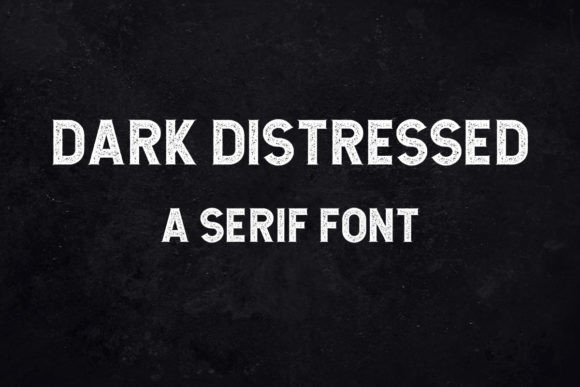
Dark Distressed
適切なデザイン要素を見つけるのは難しい場合がありますが、Dark Distressedは作品を即座に引き立てる優れたコレクションを提供します。
POD(オンデマンド印刷)製品、結婚式の招待状、またはソーシャルメディアのグラフィックを作成している場合でも、Dark Distressedは理想的です。